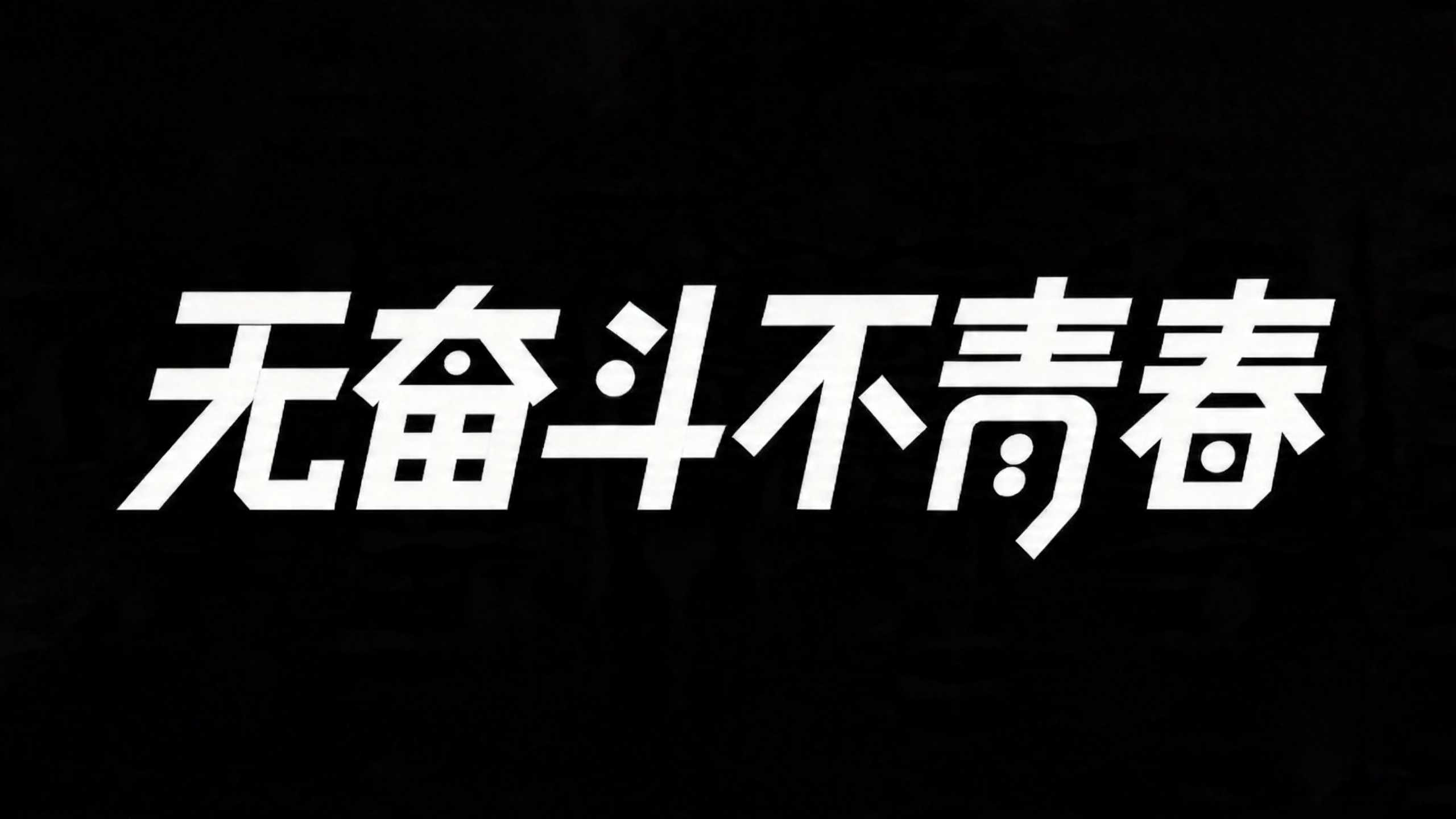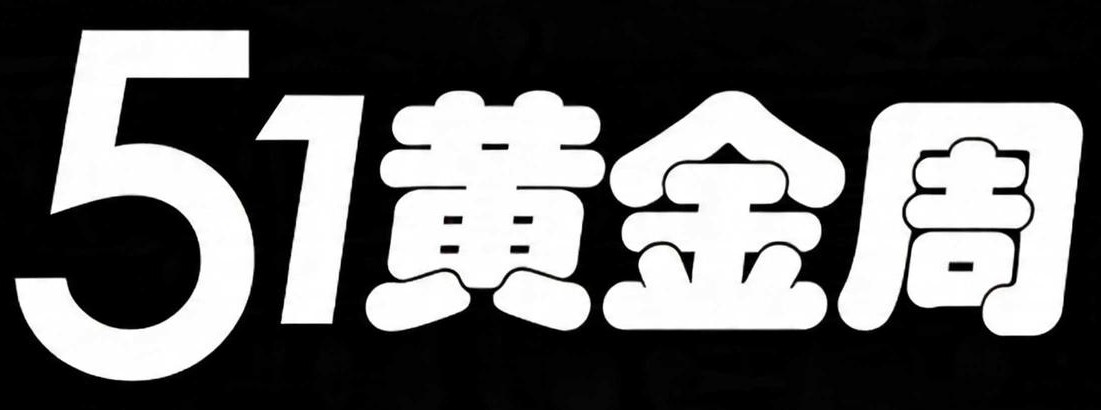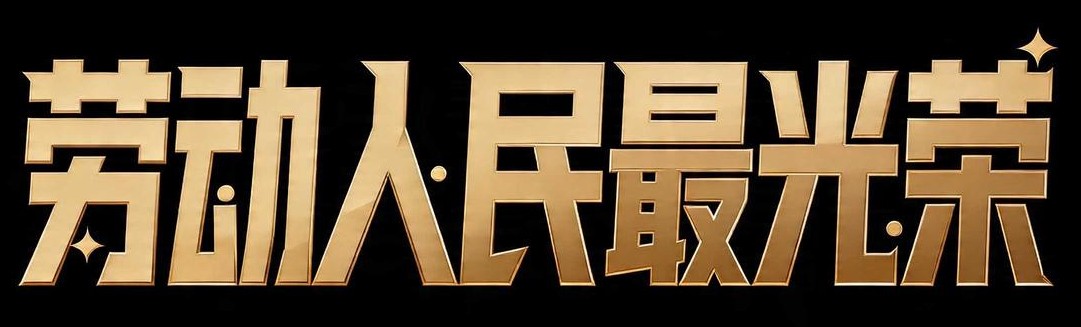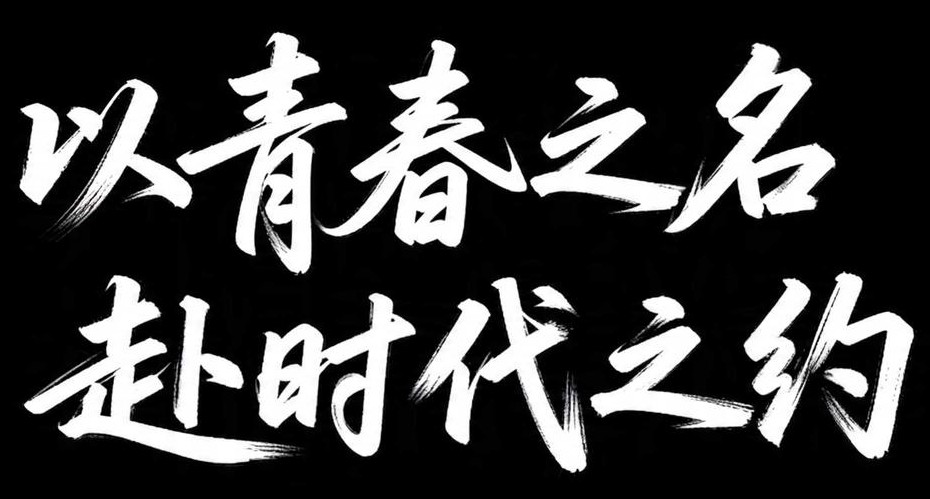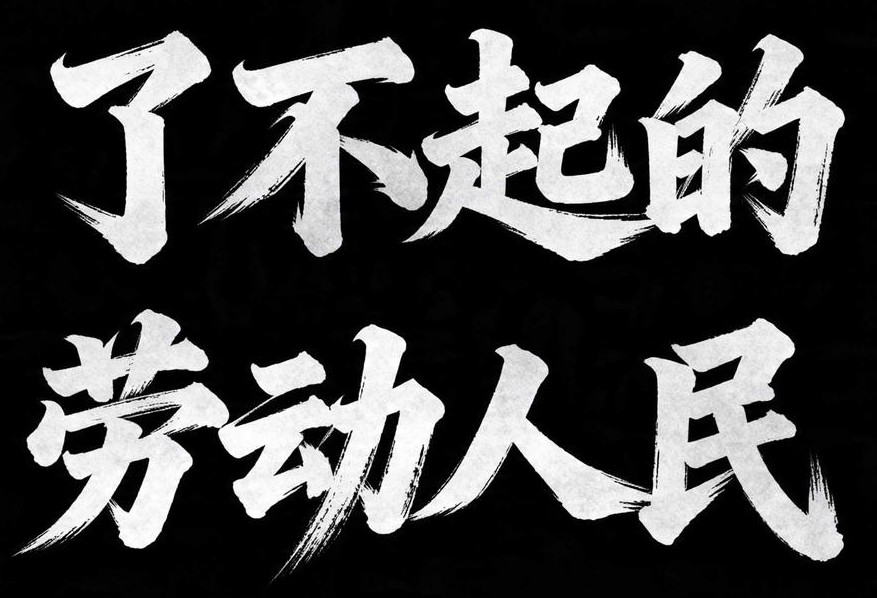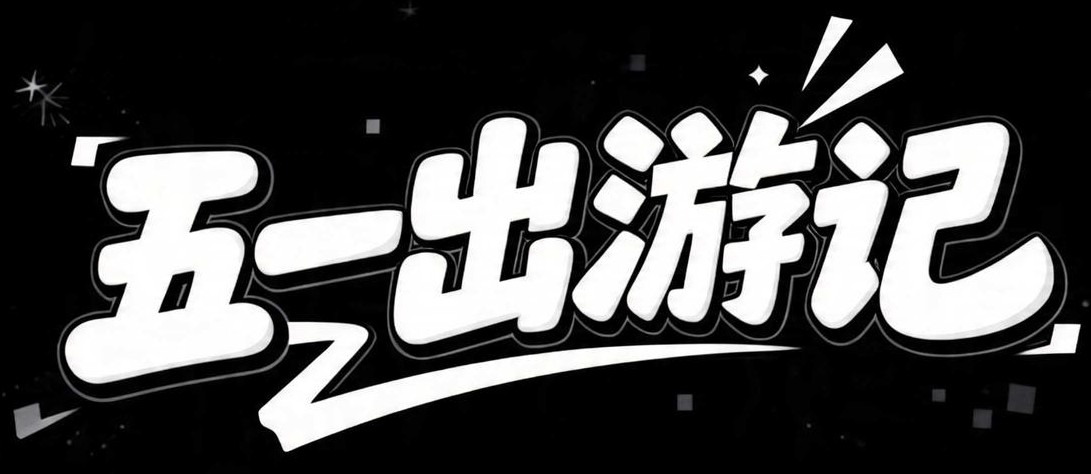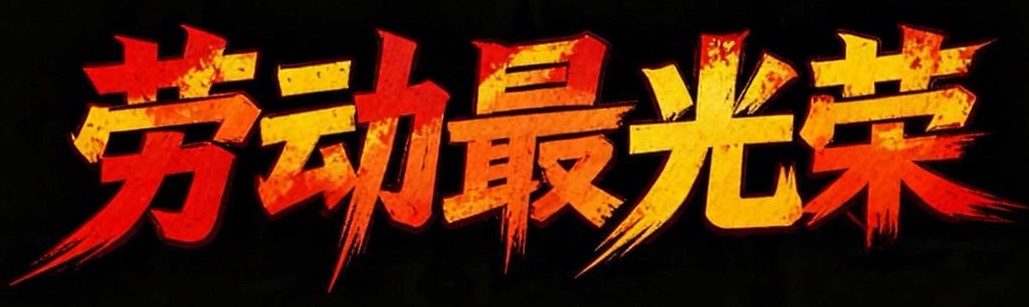
7款AI字体搞定五一黄金周和五四青年节节日海报设计!
五一假期与五四青年节即将到来,无论是事业单位、教育行业还是电商自媒体,设计们都是压力倍增啊!现在,通过字由AI字体功能,无需任何设计基础,输入口号标语即可一键生成高品质的海报标题字体。本文带来了7款五一节点AI设计字体,完美覆盖了政务宣传、教育宣传与年轻化潮流传播场景。
1.「无奋斗 不青春」:青春手绘
字体采用极具力量感和潮流感的手绘字体风格,笔画粗壮,结构紧凑,充满了年轻生命力。是五四青年节核心slogan的绝佳载体。在政务宣传与教育宣传场合,适用于机关、学校、团委的专题海报、联欢会背景板等,作为主视觉字体。也可以用于封面标题字体,非常适合作为青年主题演讲、工作报告PPT的封面标题,或微信公众号配图的首图。
2.「劳动人民最光荣」:金色庄重
这款字体呈现庄重的金色立体质感,笔划饱满,点缀的星形图案增添了仪式感。它完美融合了创意字体设计的现代感与传统口号标语的厚重感,营造出致敬与光荣的正式氛围,是五一劳动节的经典表达。推荐用于墙绘字体与黑板报:其醒目、正气的风格非常适合作为宣传栏、文化墙的创意字体设计核心。或可用于事业单位宣传物料:可用于制作奖状、光荣榜、专题宣传片的标题,彰显根正苗红的价值观。
3.「以青春之名 赴时代之约」:青春手写
字体为挥洒自如的手写字体,风格豪迈而富有生命力,适合需要展现深度与情怀的正式场合。可以用于主题教育宣传活动:用于大型纪念活动、主题展览的海报设计标题,提升整体文化格调。更推荐用于主视觉字体:作为青年论坛、主题团日活动的背景板核心文字,极具感染力。
4.「了不起的劳动人民」:书法力量
遒劲的白色书法字体,视觉庄重醒目。笔触带有飞白与手写的顿挫感,略微右倾的排版赋予静态文字一种动态的生命力,情感表达极为直接和震撼。适用于深度报道与纪录片:适合作为人物专访、纪实影像的标题。或者是高级别表彰与专题展览:用于政府或大型机构主办的劳模表彰大会、成就展的主视觉字体,风格严肃而有力。也可以用于政务宣传海报:在需要表达崇高敬意和深刻主题的正式海报设计中,这种风格能极大地提升传播的庄重感和公信力。
5.「五一出游记」:潮流活力
字体是轻松活泼的手写字体,设计充满年轻、潮流气息,直接瞄准假期消费与社交分享场景,是吸引眼球的有效创意字体设计。推荐用于商场海报与商场活动:直接用作促销活动、假日市集的海报标题字体,营造热闹氛围。甚至是小红书配图与种草笔记:作为旅游攻略、探店分享的封面标题,能有效提升点击率,极具网络传播力。
6.「劳动最光荣」:色彩渐变
这款特效字体采用斑驳质感的红黄渐变色彩,加入了现代AI设计字体的视觉特效,具有非常热血的视觉冲击力。可用于多元化海报设计:适用于从工厂车间到科技公司的各类劳动楷模表彰、企业文化宣传。或多媒体应用:可作为宣传视频的标题特效字体,或内部表彰PPT的核心视觉元素。
7.「51黄金周」:简洁促销
设计极为简洁现代,简洁有力的字体样式,舍弃冗余装饰,突出信息本身,符合快节奏商业传播的阅读习惯,视觉上干脆利落。适用于商业促销海报设计:电商广告、商场促销微信公众号配图的首选标题样式,信息传达高效。和封面标题字体:适用于各类假期促销活动清单、优惠汇总的封面设计,一目了然。